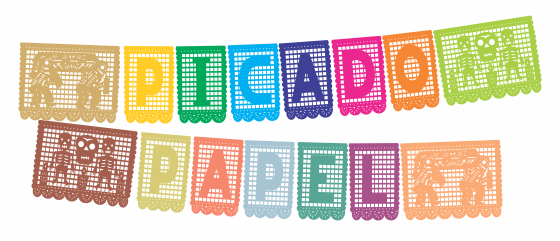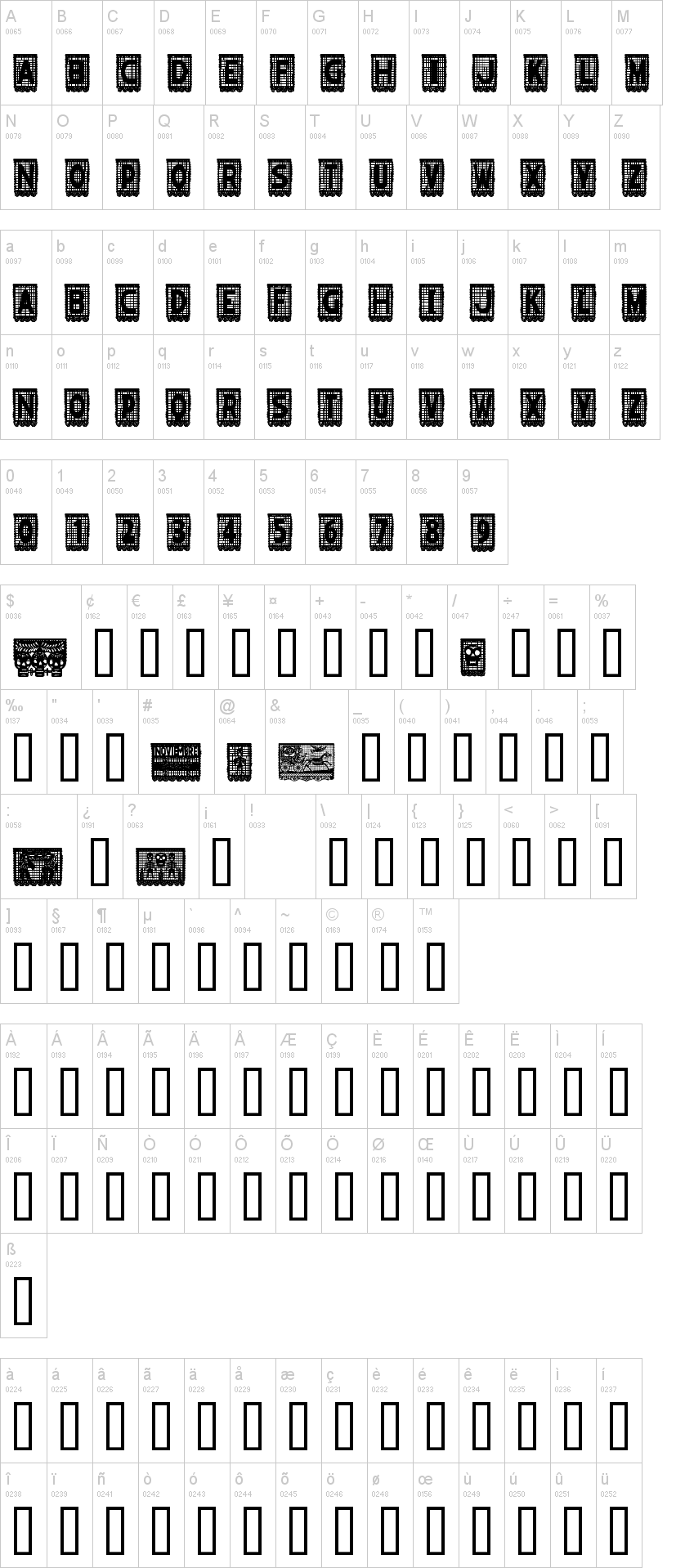
Note of the authorEsta fuente esta inspirada en el papel picado que se usa en México en festividades de Día de Muertos o en algunas fiestas de pueblos
This font is inspired paper cutting used in Mexico on Day of the Dead festivities or in some towns parties